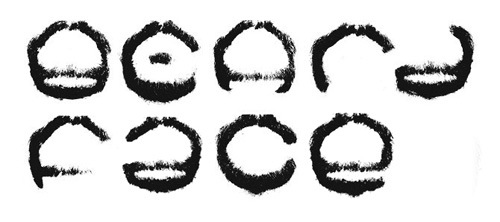
Una tipografía que está hecha afeitando las letras en una barba
Alphabeard Beardface una tipografía hecha a partir de afeitar todo el alfabeto en una barba. Vía Neatorama.